가독성 좋은 폰트가 따로 있는 게 아니라, 원리가 있더라고요
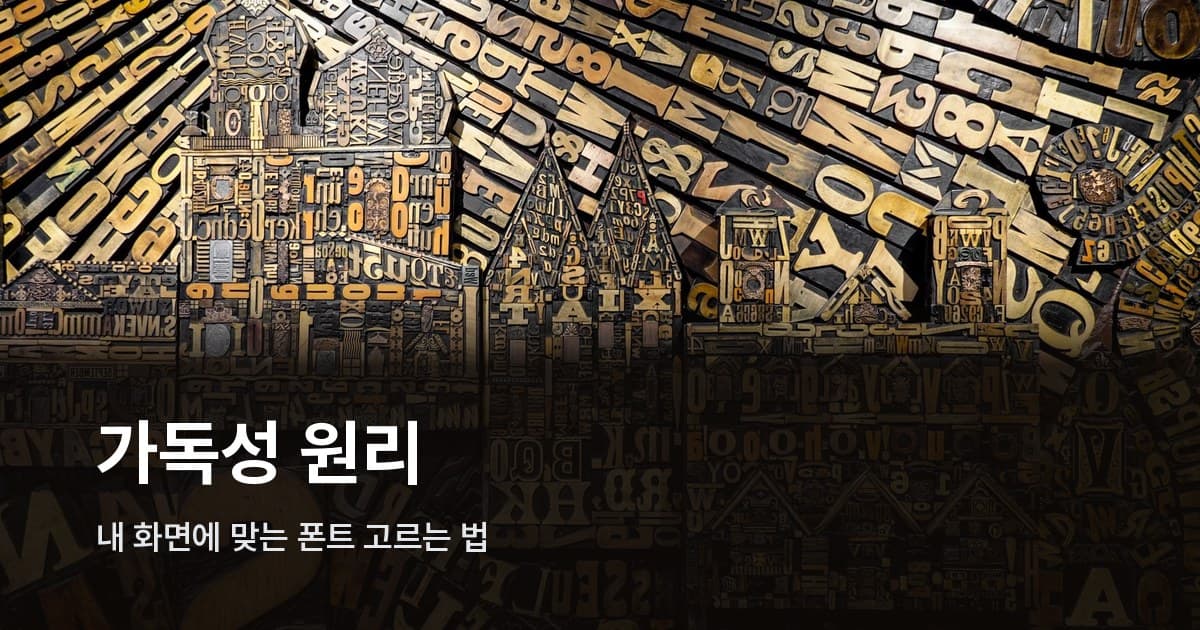
폰트를 고를 때 대부분 이렇게 하죠. 검색해서 나온 추천 목록 훑고, "이거 많이들 쓰던데" 싶으면 그냥 내려받는 거. 근데 막상 써보면 뭔가 어색해요. 분명히 많이들 쓰는 폰트인데, 내 화면에선 답답하거나 너무 빽빽해 보이거나.
그게 폰트 탓이 아닐 수도 있어요.
실제로 나눔고딕과 Noto Sans KR을 나란히 놓으면 같은 포인트 크기인데 하나가 훨씬 더 크게 보여요. 같은 12px인데 말이에요. "내 눈이 이상한가?" 싶었는데, 알고 보니 폰트가 설계된 방식이 달라서 생기는 차이더라고요.
"좋은 폰트"를 가져왔는데 왜 내 화면에선 안 맞나
폰트 추천 글에서 1등 찍은 폰트를 그대로 적용했는데도 내 글이 답답해 보이는 건, 폰트가 나쁜 게 아니라 그 폰트가 설계된 상황과 내가 쓰는 상황이 다른 것이에요.
추천 목록은 보통 폰트 자체의 완성도를 평가하지, 내 콘텐츠의 크기·매체·독자층과 맞는지를 알려주지 않아요. 일반적으로 "가독성 좋다"는 평가를 받는 폰트도, 8pt 인쇄 문서에 쓰면 얇은 획이 사라지거나 자소가 뭉쳐 보일 수 있어요. 반대로 화면에서 빽빽해 보인다고 인쇄용 명조로 바꾸면, 저해상도 모니터에서 오히려 더 읽기 어려워지죠.
이 문제를 근본부터 풀려면 폰트 설계자가 실제로 어떤 변수를 조율하는지 알아야 해요. 변수를 알고 나면, 추천 목록 없이도 내 상황에 맞는 폰트를 직접 판단할 수 있거든요.
폰트 안에서 실제로 조율되는 네 가지 변수
판독성(Legibility)과 가독성(Readability)은 다른 개념이에요. Google Fonts Knowledge에서도 이 둘을 따로 설명해요. 판독성은 글자 하나를 얼마나 정확하게 식별하는지, 가독성은 단락 전체를 얼마나 편하게 읽는지의 문제예요. 장식이 많은 디스플레이 폰트는 제목 한 줄에선 판독성이 높지만, 본문 단락으로 쓰면 금세 눈이 피로해지죠.
폰트 설계자는 아래 네 가지 변수를 조율해서 이 둘 사이의 균형을 잡아요.
글자 몸통 비율(em box 대비)
영문 타이포그래피에서 x-height는 소문자 몸통이 차지하는 높이예요. 한글은 대소문자 구분이 없는 네모틀 구조라 직접 적용되진 않지만, 글자틀(em box) 안에서 실제 글자가 차지하는 비율이 비슷한 역할을 해요. KCI 등재 논문에 따르면 글자틀높이를 활자틀높이 대비 90% 이상으로 설정해야 폰트 간 크기 호환이 어긋나지 않는다고 해요. 같은 12px인데 나눔고딕이 Noto Sans KR보다 작아 보이는 건, 이 비율 설계가 달라서예요.
열린 틈(어퍼처)
어퍼처(aperture)는 획이 열려 있는 부분의 폭이에요. 영문의 'c', 'e'에서 잘 드러나고, 한글에선 'ㄹ'의 꺾임 부분이나 'ㅂ', 'ㅎ' 내부 공간에서 비슷한 원리가 작동해요. 이 틈이 좁으면 소형 크기나 저해상도에서 유사 자소끼리 뭉쳐 보여요. 'ㄹ'과 'ㄷ'이 구분 안 가거나 'ㅂ' 안쪽이 막혀 보이는 증상이 대표적이에요.
굵기 차이(획 대비)
획 대비(stroke contrast)는 가장 굵은 획과 가장 얇은 획의 두께 차이예요. 명조(Serif)는 크고, 고딕(Sans-serif)은 작거나 거의 없어요. 웹·앱 본문에 고딕이 압도적으로 많이 쓰이는 건 트렌드가 아니라 구조적 이유가 있어요. 고대비 서체의 얇은 획은 저해상도 화면에서 그냥 사라져버리거든요. 반대로 인쇄물에서는 고대비 서체가 글자에 리듬감을 줘서 장문 독서 피로를 오히려 낮춰줘요. 한글은 받침이 있는 글자 구조상 획이 촘촘하게 쌓이는 경우가 많아서, 한글 명조 계열은 8pt 이하 인쇄에서 얇은 획이 먼저 사라지는 위험이 실제로 있어요.
글자 내부 흰 공간(카운터)
카운터(counter)는 'ㅇ', 'ㅁ', 'o', 'p'처럼 글자 안쪽에 둘러싸인 흰 공간이에요. 나눔고딕을 14px로 쓰다가 Noto Sans KR로 바꾸면 숨이 트이는 느낌이 드는데, 폰트를 바꿨더니 "글자가 더 선명해졌다"는 반응이 나오는 경우 대부분 이 카운터 차이가 원인이에요. 한글에서 'ㅇ'은 초성·중성·받침까지 한 글자 안에 여러 번 나올 수 있어요. '왕', '옹' 같은 글자를 작은 크기로 보면 내부가 빽빽하게 채워진 것처럼 보이는 게 이 때문이에요. 고령 사용자나 시각 저하 사용자에게는 이 차이가 특히 크게 느껴지고요.
'전부 고딕'이어도 설계 방향이 왜 이렇게 다를까
네 가지 변수를 알고 나면, 전부 고딕이라도 각 폰트가 어떤 상황을 위해 설계됐는지 보여요.
Noto Sans KR(본고딕)은 모바일 화면 최적화에 집중한 폰트예요. 글자 몸통이 em box 안에서 크고, 획 대비가 낮아 화면 가독성을 우선했어요. 카운터 공간이 넉넉한 편이라 작은 크기에서도 자소가 뭉치지 않아요. 복잡한 자소에서도 내부 공간을 충분히 확보해서 스마트폰 본문용으로 가장 널리 쓰이는 폰트 중 하나예요.
Pretendard는 본고딕 한글 구조를 기반으로 영문을 Inter에서 가져와 다듬은 폰트예요. 굵기가 9단계라 웹·앱 UI에서 계층 표현 폭이 넓고, system-ui 대체 글꼴로 설계돼서 화면 렌더링 최적화가 잘 되어 있어요. 한글·영문 혼용이 많은 서비스 UI에 특히 잘 맞아요.
KoPubWorld 돋움은 한국출판인회의(KOPUS)가 전자책·출판 환경에 맞게 설계한 폰트예요. 장문 읽기에 어울리는 설계라 전자책 리더기처럼 낮은 해상도 환경에서 빛을 발해요.
나눔고딕은 낮은 해상도 화면에서도 획이 유지되도록 힌팅 처리가 잘 되어 있고, 웹 본문과 인쇄물 모두에서 무난하게 쓸 수 있어요. 다만 글자 몸통 비율이 Noto Sans KR보다 작은 편이라, 같은 크기에서 조금 작아 보이는 건 감안해야 해요.
실수가 나는 지점이 여기예요. Noto Sans KR은 화면용으로 설계된 폰트인데, 이걸 8pt 인쇄 소책자에 그대로 쓰면 카운터 설계가 인쇄 환경에서 기대한 대로 작동하지 않을 수 있어요. KoPubWorld 돋움은 전자책 리더기 해상도를 기준으로 최적화된 폰트라, 고해상도 모니터에선 약간 심심하게 느껴지기도 하고요. "인기 폰트=내 상황에 맞는 폰트"라는 등식이 깨지는 게 딱 이 지점이에요.
내 폰트가 맞는지 스스로 진단하는 체크리스트 ✓
원리를 알고 나면 폰트를 직접 판단할 수 있어요. 용도별로 확인 포인트가 달라요.
소형 크기(12~14px) 화면 본문용
- 동일 크기 다른 폰트와 나란히 뒀을 때 글자가 작아 보이지 않는가 (em box 대비 몸통 비율)
- 'ㄹ', 'ㅂ', 'ㅎ', 'ㅇ' 같은 복잡한 자소가 뭉개지거나 달라붙어 보이지 않는가
- 얇은 획이 사라지지 않는가 (획 대비가 낮은 고딕 계열 권장)
- 유사 자형('ㅁ'과 'ㅂ', 'ㄹ'과 'ㄷ')이 서로 헷갈리지 않는가
인쇄 본문(8~10pt)용
- 인쇄 후에도 얇은 가로획이 살아있는가
- 'ㅇ', 'ㅁ' 같은 글자 내부가 작은 크기에서 메워 보이지 않는가 (카운터 공간)
- 종이 재질과 인쇄 방식에 획 대비가 맞는가 (고급지 → 세리프 허용, 저해상도 레이저 프린터 → 고딕 권장)
제목·캡션(16px 이상)용
- 이 크기에서는 얇은 획이 충분히 유지되는가
- 자간이 자연스러운가 (너무 좁으면 제목에서도 답답하게 느껴짐)
- 굵기(weight) 옵션이 있어 본문과 위계 구분이 가능한가
한 가지 더 — WCAG 2.1 기준에서 일반 본문 텍스트는 배경과 최소 4.5:1의 명도 대비가 필요해요. 18pt(굵은 14pt) 이상의 큰 텍스트는 3:1까지 완화되고요. 폰트 설계와 배경색 대비, 이 두 축이 같이 맞아야 진짜 가독성이 나와요.
추천 목록 없이도 직접 판단할 수 있게 되는 순서
폰트 추천 목록은 계속 바뀌어요. 새 폰트가 나오고, 트렌드가 이동하고, 플랫폼이 달라지면 추천도 달라지죠. 내 콘텐츠의 조건을 반영한 추천은 결국 내가 직접 해야 하고요.
판단 순서는 이래요. 먼저 매체를 정해요. 화면인지 인쇄인지에 따라 획 대비 기준이 뒤집히니까요. 다음으로 사용 크기를 확인해요. 12px 모바일 본문과 8pt 소책자 인쇄는 카운터와 어퍼처에서 요구하는 기준이 달라요. 마지막으로 대상 독자를 생각해요. 고령 독자나 시각 저하 사용자가 있다면 카운터 공간을 더 넉넉하게 잡아야 하고, 이 경우 글자 몸통 비율이 높은 폰트를 우선해야 해요.